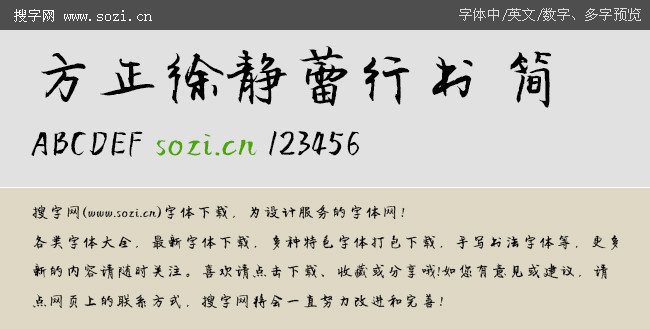
方正徐靜蕾行書(shū)簡(jiǎn)
搜字網(wǎng)提供一款方正徐靜蕾行書(shū)簡(jiǎn)中文字體下載,方正徐靜蕾行書(shū)由知名影視演員、導(dǎo)演徐靜蕾創(chuàng)作。這款字是靜蕾體推出十年后創(chuàng)作的。徐靜蕾自幼習(xí)書(shū),有十年顏體功底,這款行書(shū)體繼承了靜蕾體骨骼,結(jié)構(gòu)清秀、遒勁有力,個(gè)性優(yōu)雅從容。適用于現(xiàn)代詩(shī)歌、短文的排版,以及文化、商業(yè)類品牌的廣告語(yǔ)設(shè)計(jì)。
- 風(fēng)格類別: 手寫書(shū)法體